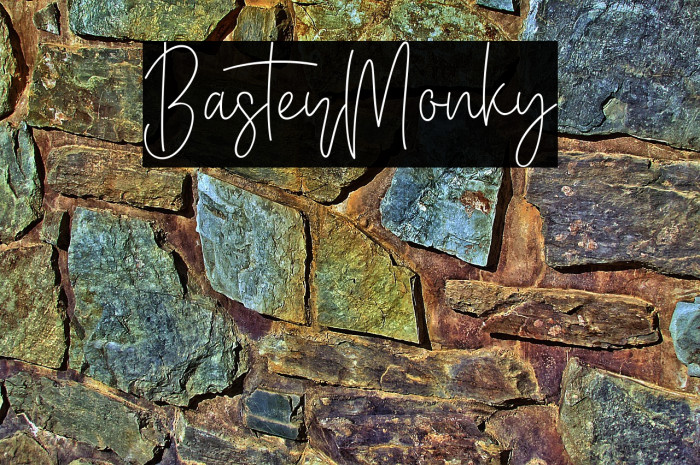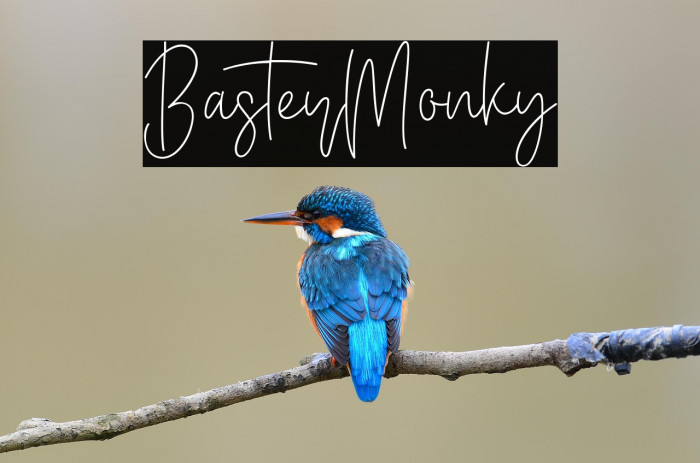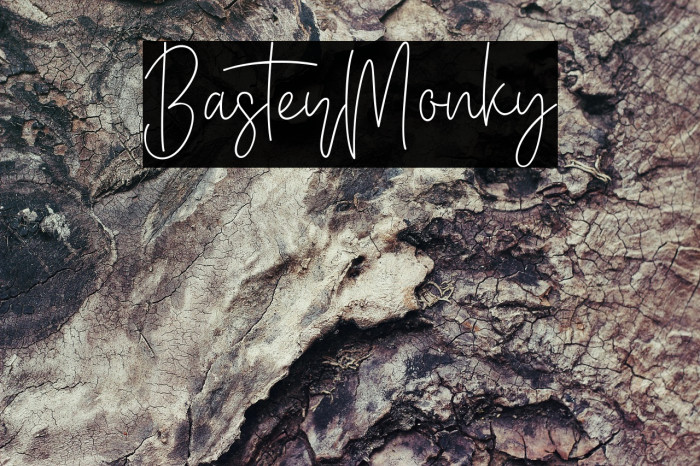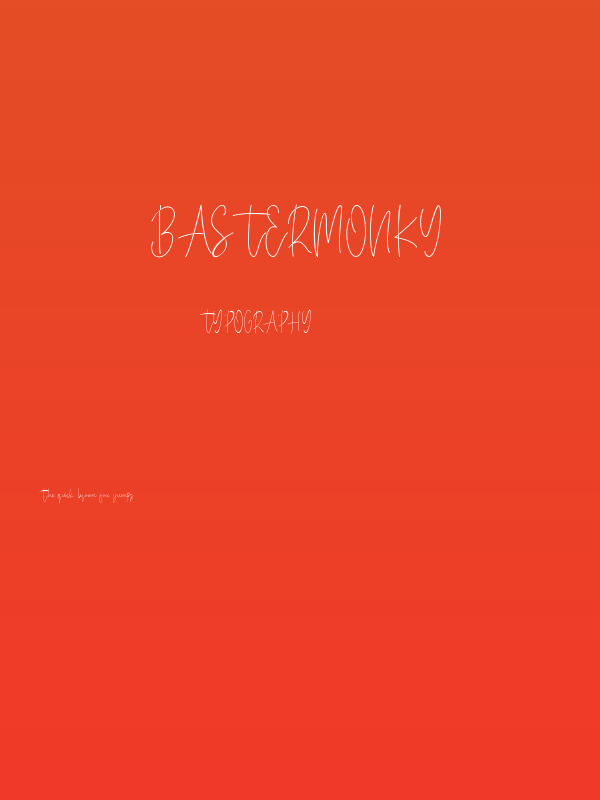
BasterMonky Font
| Caso d'uso | Logos, Headlines, Creative projects |
| Progetti proposti | Ideal for greeting cards, invitations, personal branding, and creative projects that require a whimsical touch. |